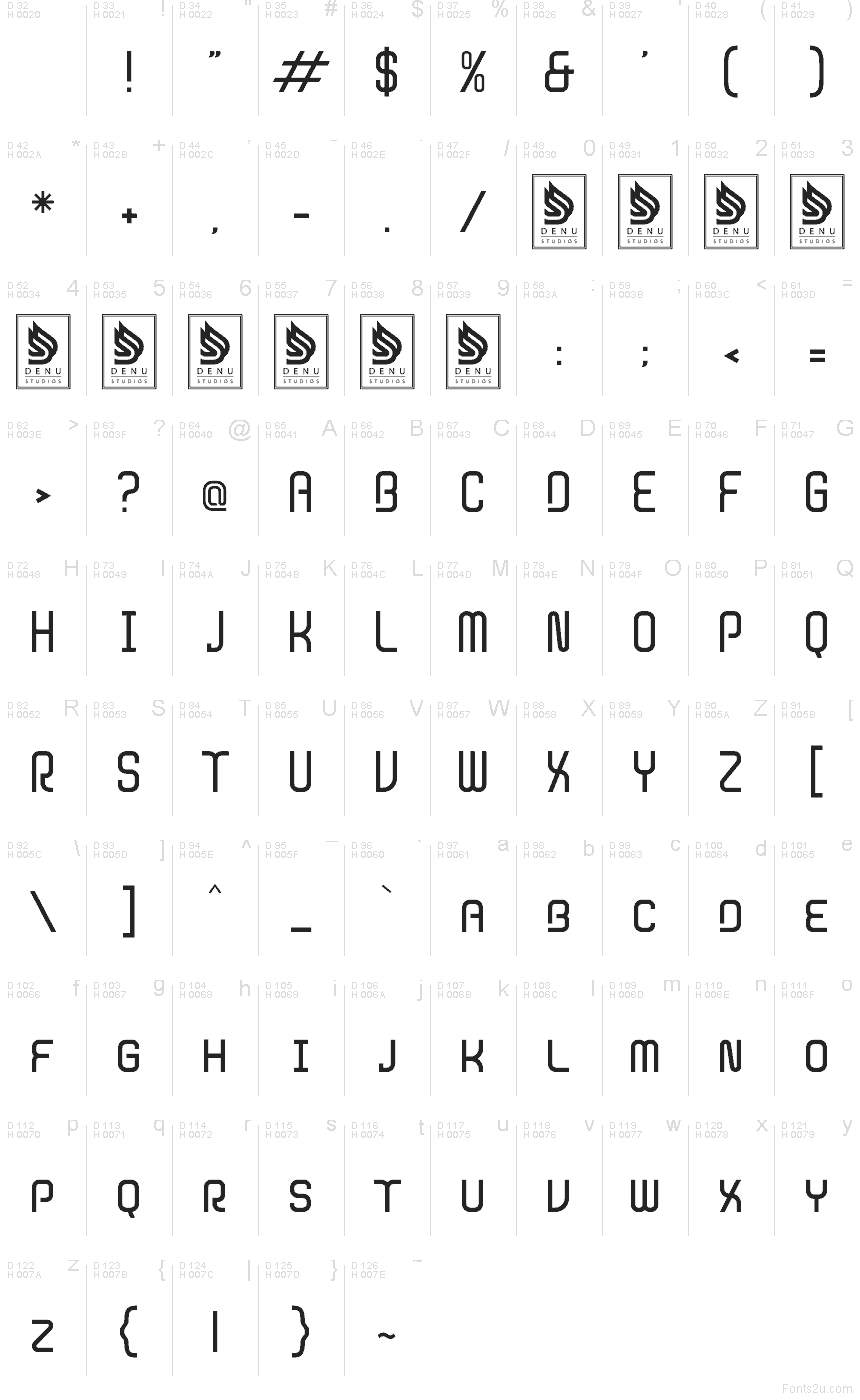
Klown Void de Denustudios es una tipografía display futurista con un ritmo casi modular. Las letras se sienten minimalistas y sintéticas, con formas altas y redondeadas, uniones estrechas y algunos cortes afilados que evitan que el resultado se vuelva demasiado amigable o retro.
Encaja a la perfección en pósteres tecnológicos, gráficos para videojuegos, portadas de música, títulos en movimiento y marcas que buscan un tono elegante y diseñado. Al ser una fuente gratuita, también funciona muy bien para titulares cortos y logotipos, ya que sus verticales redondeadas repetitivas y sus curvas recortadas le dan a cualquier línea un pulso electrónico controlado.